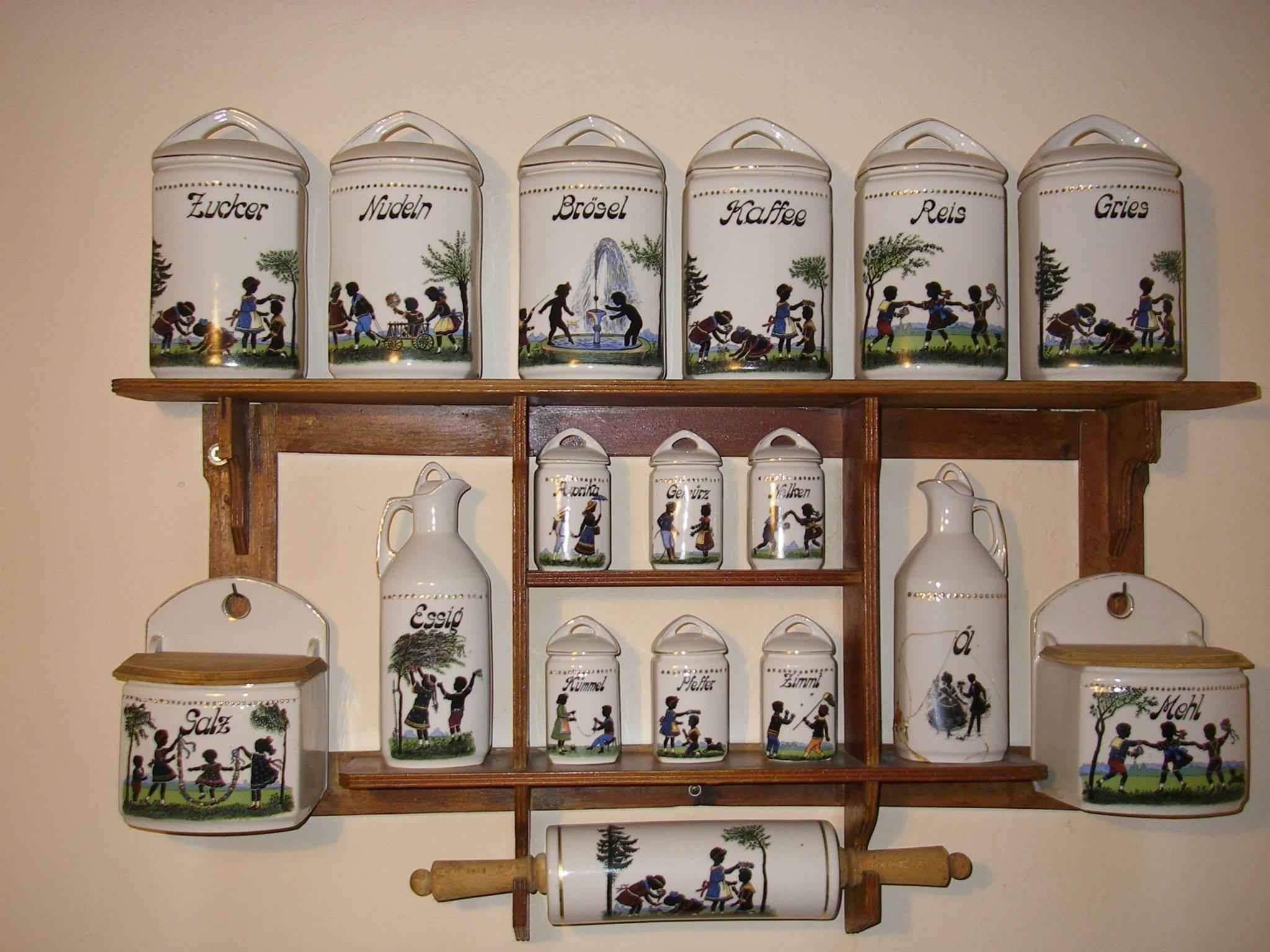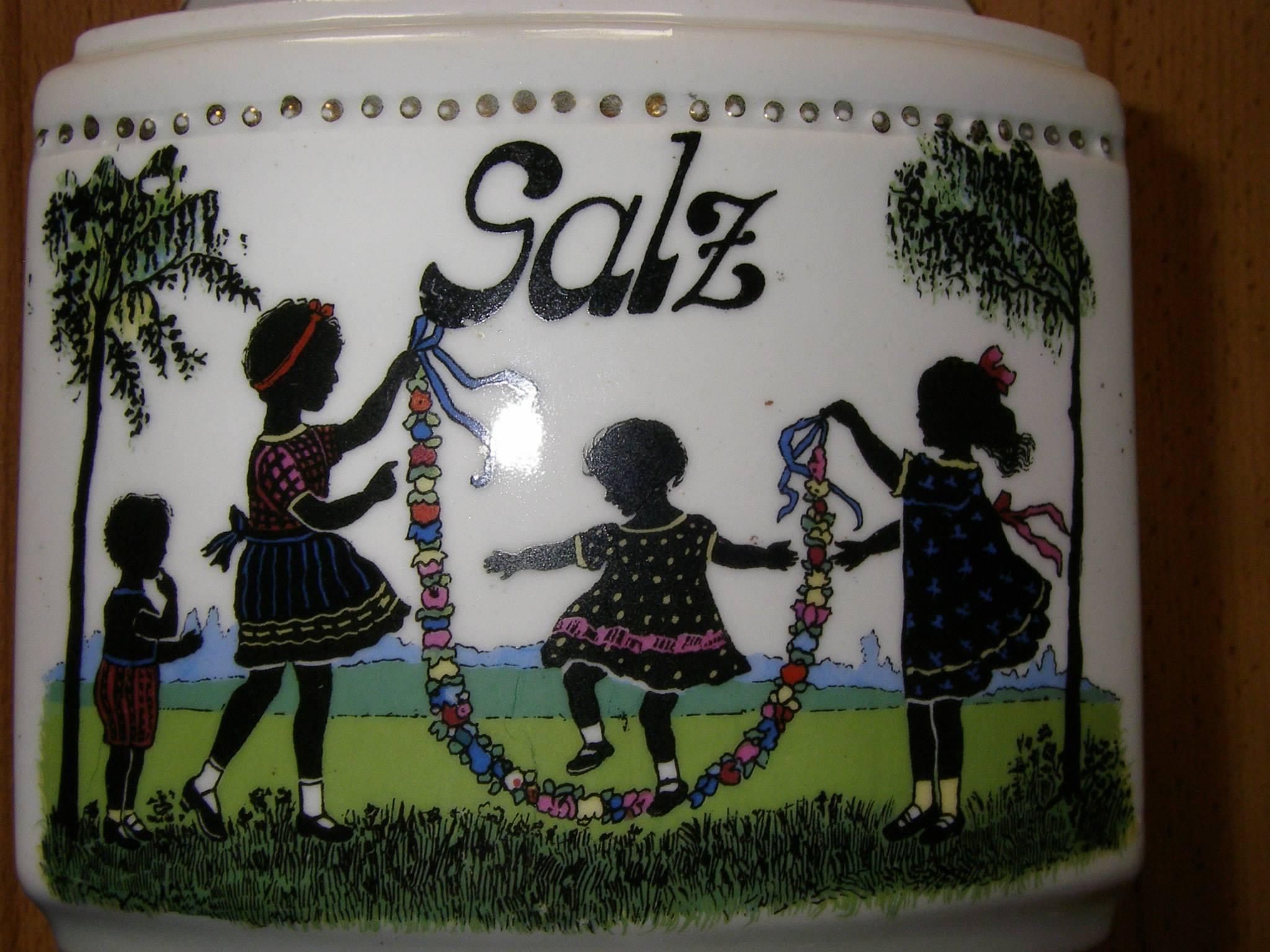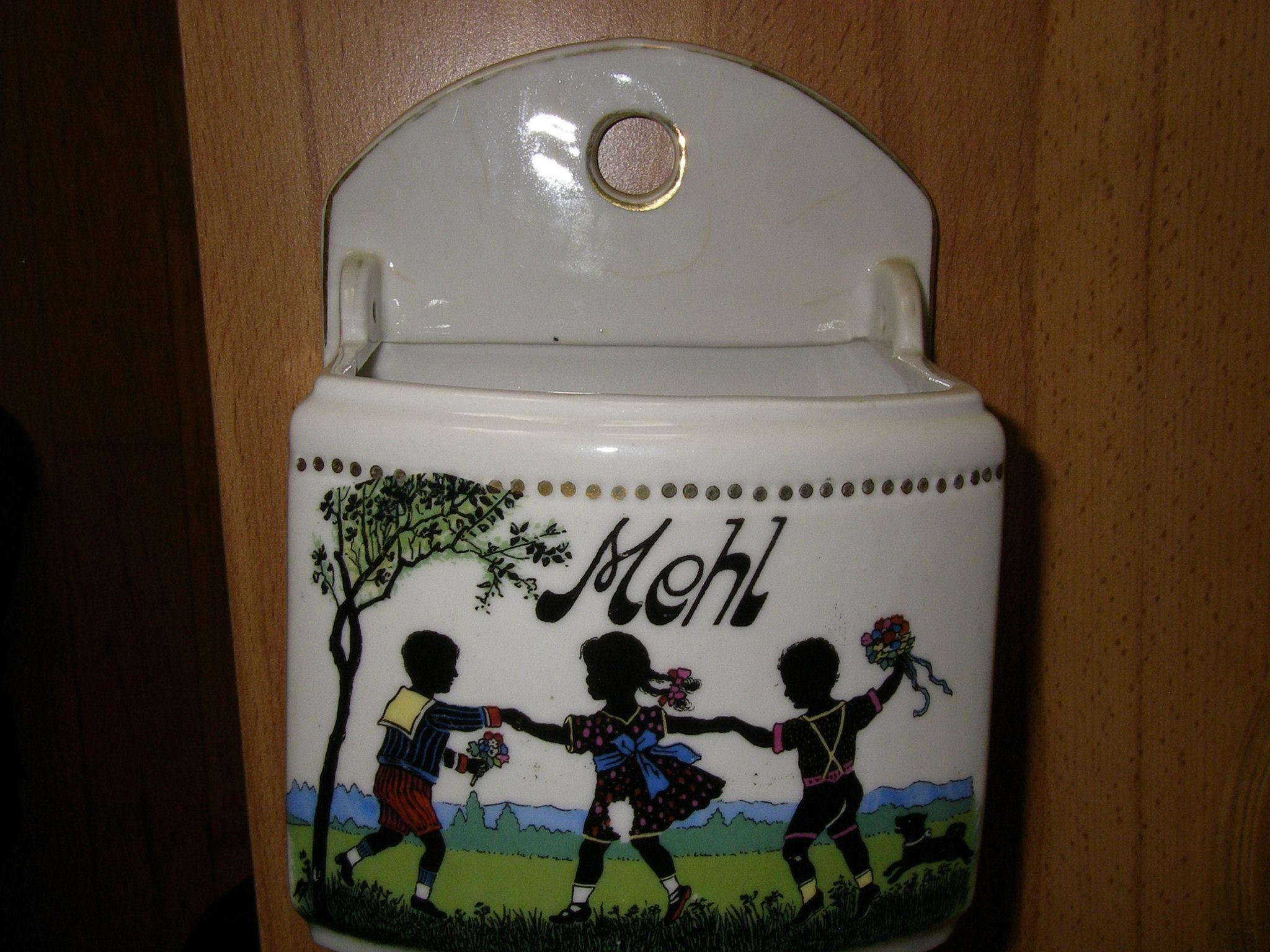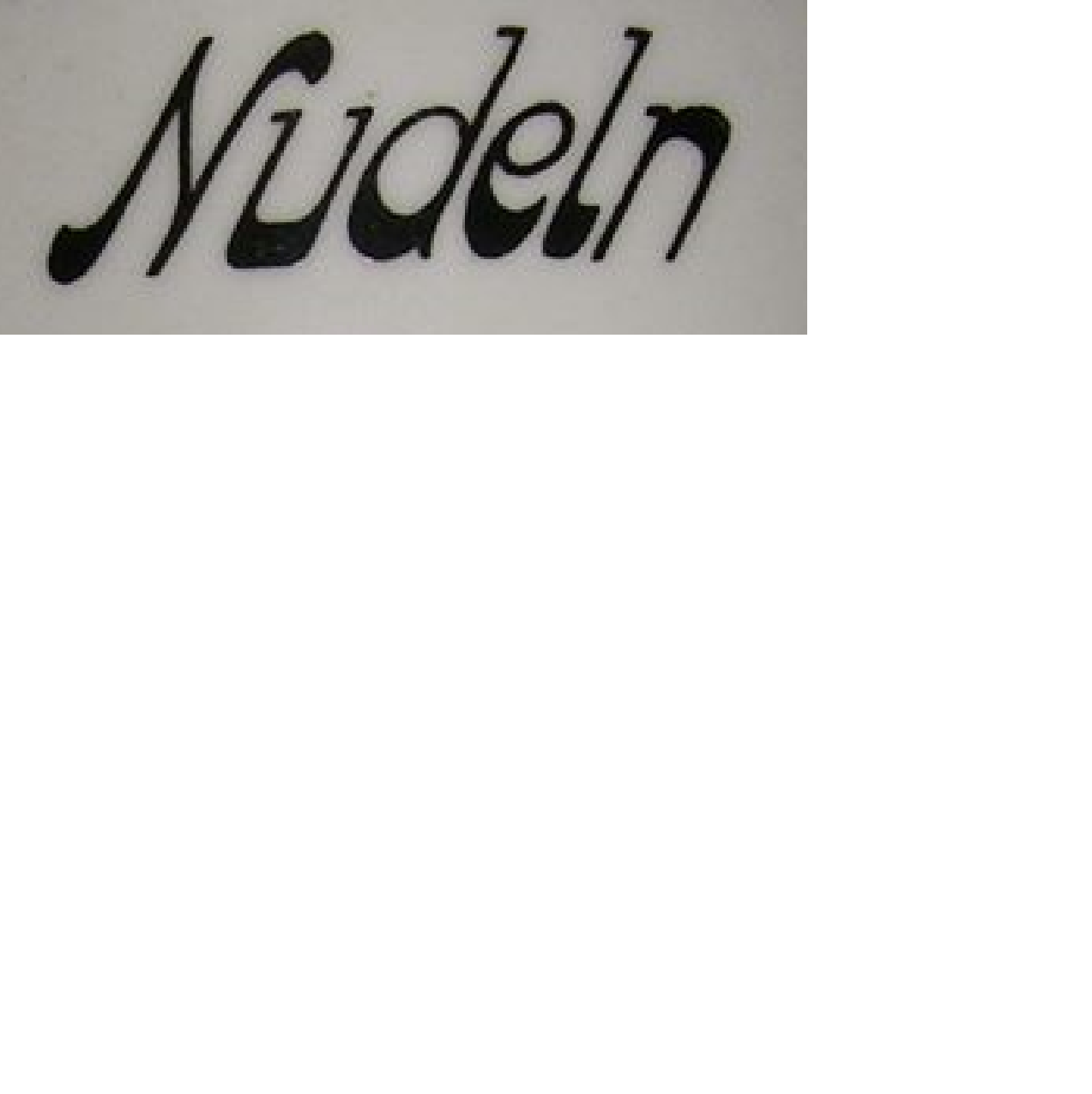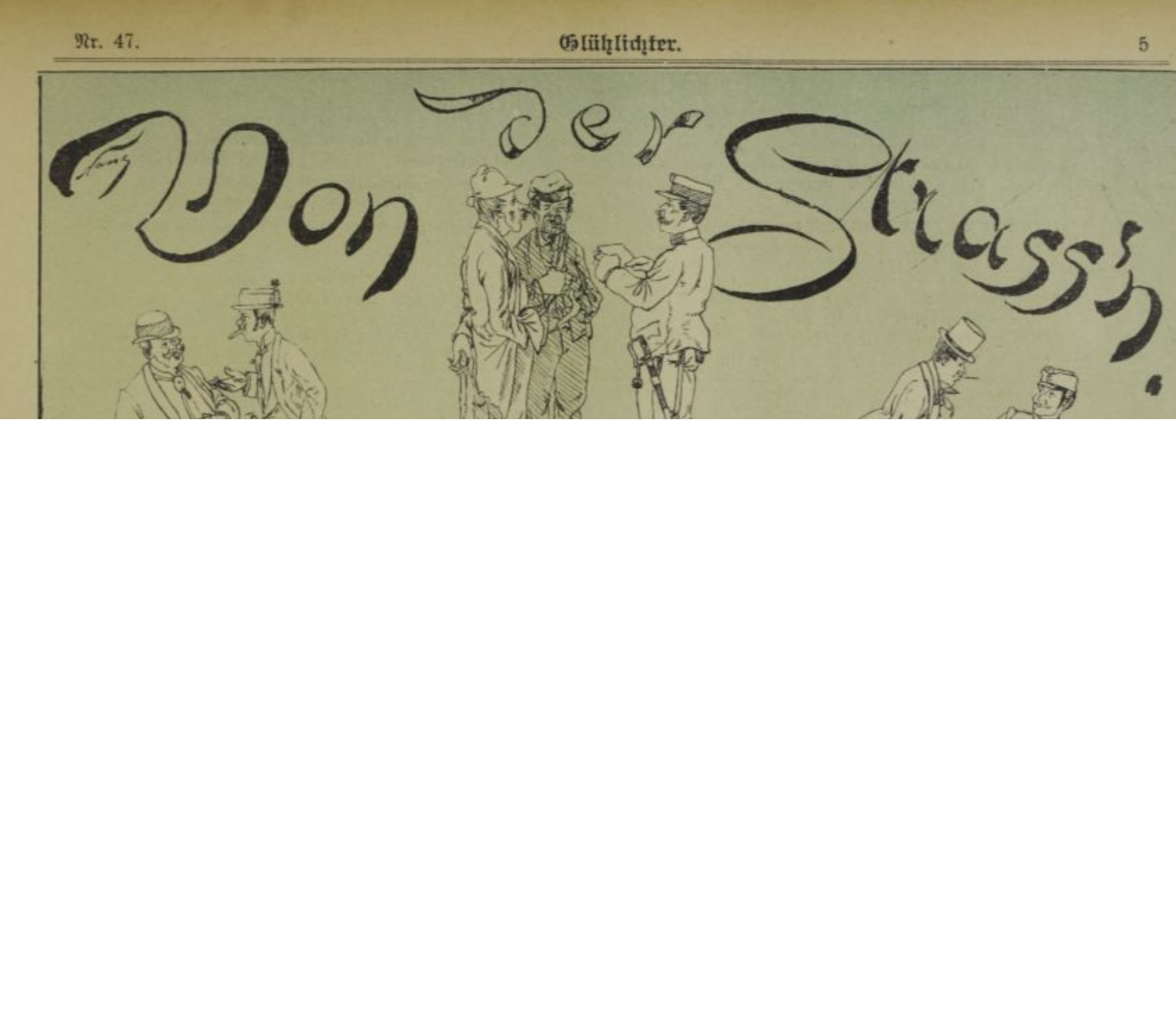
Alter und Herkunft einer Porzellan-Aufschrift über Schriftform bestimmen?
ich habe ein Erbstück mit einer Beschriftung in Jugendstil-Buchstaben.
Ich vermute ich kann das Alter und die Herkunft über die Schriftform bestimmen, ich bitte um ihre Unterstützung.
Die Kunstwerke auf dem Porzellan sind von dem Künstler
Friedrich Kaskeline (* 8. Mai 1863 in Prag; † nach 1931)
Woher kommt diese Schriftform und wie alt ist die Schriftform?
Wirklich schönes Teil. Nun, ich bin ja in einer Familie aufgewachsen, in der mit solchen Dingen gehandelt wurde. Daher habe ich schon so einige solcher Küchen- Zutaten-Lagersätze gesehen, aber das ist wirklich ein besonderes Teil.
Was die Schrift anbelangt, wurde diese ganz speziell für dieses Arrangement gezeichnet, es ist keine Satzschrift und beruht auch nicht auf einer, es wäre also bestenfalls umgekehrt möglich, aus dieser Vorlage auch eine Schrift zu entwickeln.
Ich schätze dieses Teil auf etwa Mitte der 20er Jahre des letzten Jahrhunderts, auch vom Stil der Kinderkleidung her, denn ich habe Fotos meiner Mutter und ihrer Brüder aus dieser Zeit, und darauf sind sie sehr ähnlich gekleidet.
Befindet sich unten auf den Töpfen und Behältern eine Porzellan-Marke, die du hier einstellen könntest, denn ich besitze noch die Porzellan-Erkennungsbücher meiner Mutter, findet man die Marke, kann man nämlich noch genaueres sagen.
Auch die, von der heutigen Orthografie abweichenden, Schreibweisen von »Zimmt« und »Gries« können bei der Datierung helfen.
Zeitlich würde ich die Entstehungszeit der Schrift nach den Formen um 1900 einsortieren, also Jugendstil/Art Noveau/Wiener Secession etc.
Zimt wurde bis zur 2. Orthographische Konferenz 1901 mit zwei m geschrieben. Danach offiziell mit nur einem. Wie lange es aber gebraucht hat, bis sich alle daran hielten, weiß keiner …
Die Kinder auf den Bildern haben ja auch noch (schematisierte) spätwilhelminische Kleidung an ...
Ich würde das Set wohl auf die Zeit zwischen Fin de Siècle und 1. Weltkrieg schätzen.
Ich hab mal ein wenig gestöbert – die meisten kolorierten Scherenschnitte von Kaskeline in diesem Stil hab ich von ab 1920 gefunden, also nach dem 1. Weltkrieg. Meist sind’s Postkarten. Meine Vermutung für das Gewürzregal wäre daher eher ab 1920.
Ich hab sogar eine der direkten Vorlagen für die Einbrennabziehbilder gefunden, auch eine Postkarte, aber leider undatiert ;-)
Die AK "Pfingstfest" ist bei Wilh. Schröder & Söhne, Berlin (WSSB) erschienen, mit der Serien-Nr. (?) 5862. AK aus demselben Verlag mit Seriennummern knapp über 5000 stammen wohl aus der Zeit um 1914. Wenn ich weitere Webfunde richtig deute, sind Kaskelines Karten nach 1920 (auch?) in einem anderen Verlag (evtl. Heliophot, Berlin) erschienen. Insofern kommt wohl doch eher ein Zeitraum von 1918 bis 1930 für das Regal infrage.
Nachtrag: Die altertümliche Schreibung von Zimmt und Gries spricht nicht dagegen, die findet man noch auf vielen Gewürzschütten (im Web, sic) bis in die 30er ...
Ich hoffte die Schriftform würde bekannt sein, wenn der Schriftzug eine extra Anfertigung ist finde ich das auch gut.
Ich finde die Schrift und die Motive sind angenehm für die Augen.
Schade das es diese Schriftform nicht mehr gibt.
Auf der Suche nach der gebrochenen Ölkanne habe ich nichts Vergleichbares gefunden.
Ob es wirklich fast 100Jahre alt ist? Ich bin skeptisch und hoffte die Schriftform wird mir Fakten liefern.
Auf der Unterseite der Behälter ist eine Press marke „Sonja“ alle ohne Stempel. Manche Behälter haben unten 2 Kerben.
Ich habe leider kein gutes Bild von dem Press-stempel der Unterseite, der Press-stempel ist in einer etwas anderen Schrift vielleicht kann die Stempel Schrift helfen.
Ich sehe da nur 2 s, dafür aber einen Apostroph als Auslassungszeichen für ein e: Strass’n
Wenn Kokain Künstler wie Falco, Wecker, Fendrich oder der Springer Andreas Goldberger zu ihrem Konsum was sagten, war es immer a Strass sn Koks. Ich seh(e) ein hochgestelltes s.
zu den Bilder, kaum ein Rätsel gelöst kommt ein neues auf mich zu.
In der Wespe auf der Kümmel Dose.
Die Signatur hat mich an ein anderes Bild in den Glühlichtern erinnert.